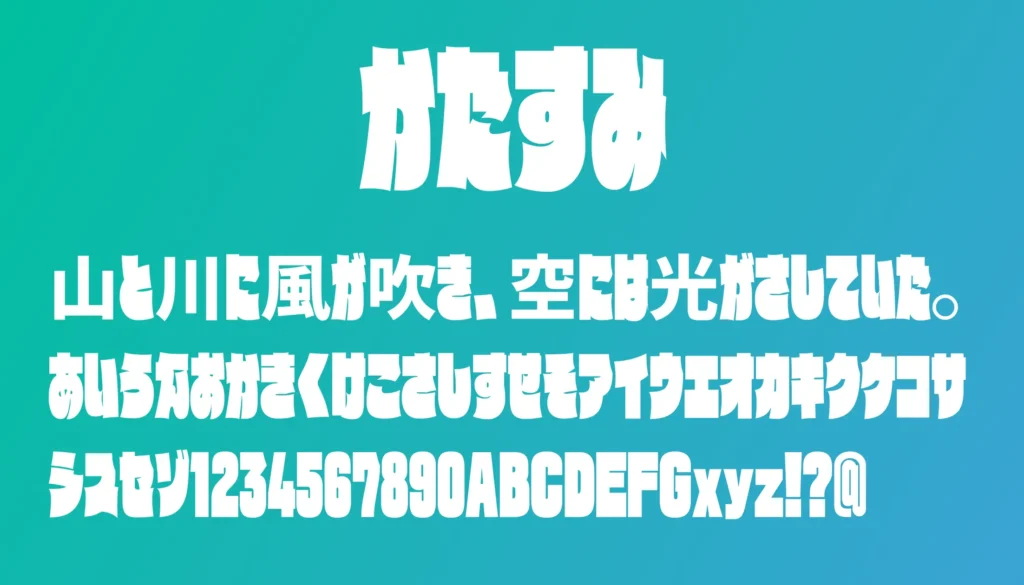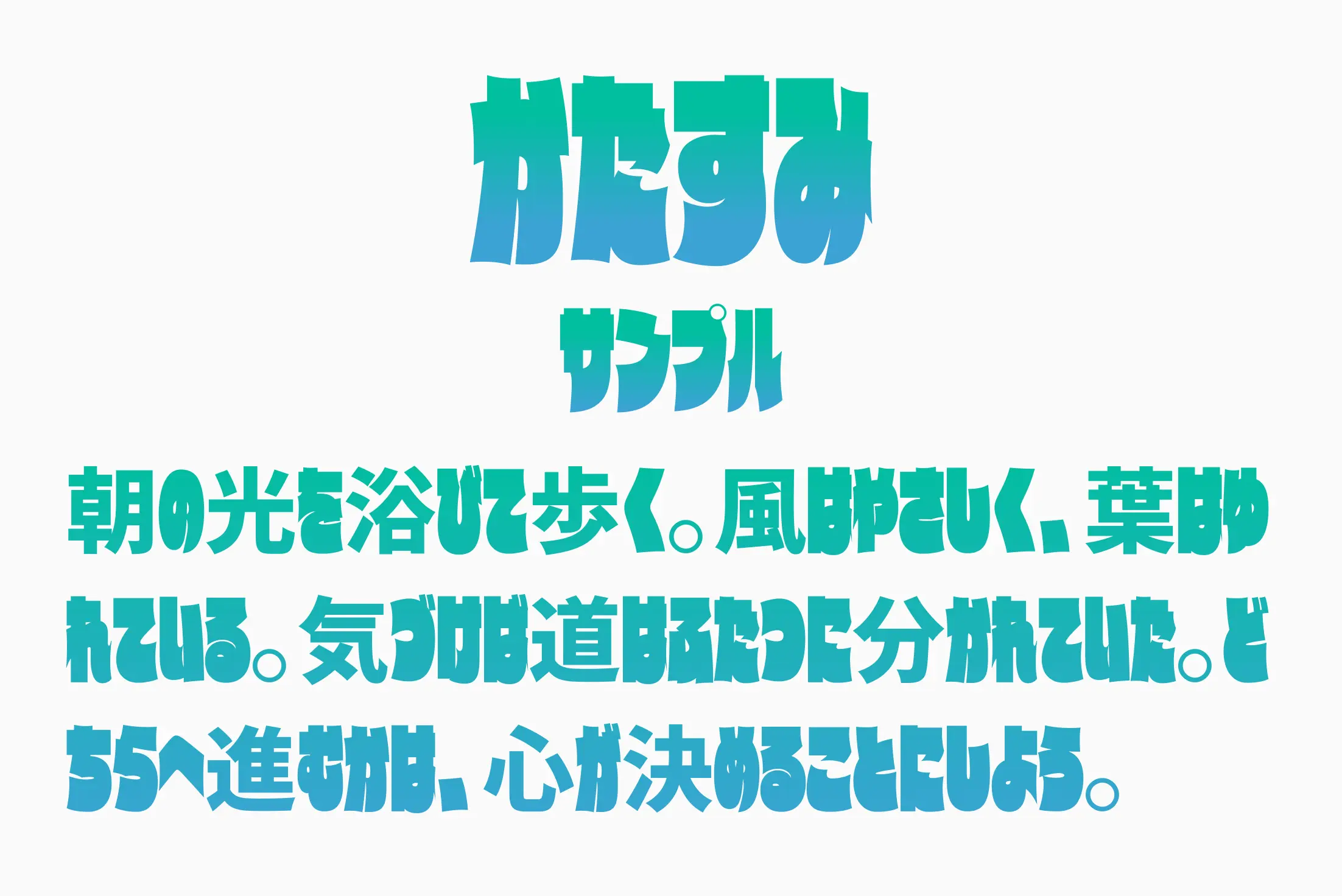
文字幅を極限までスリムに設計した個性的な極太かなフォントです。ぎゅっと圧縮されたような独特のシルエットが特徴で、限られたスペースでも圧倒的な存在感を発揮します。一般的な極太フォントでは表現しにくい密度感や迫力を演出できるため、ポスターやバナー、動画サムネイルなど視線を集めたいデザインにぴったり。漢字フォントと組み合わせることで、インパクトのある見出しやタイトルを手軽に作ることができます。
かたすみ